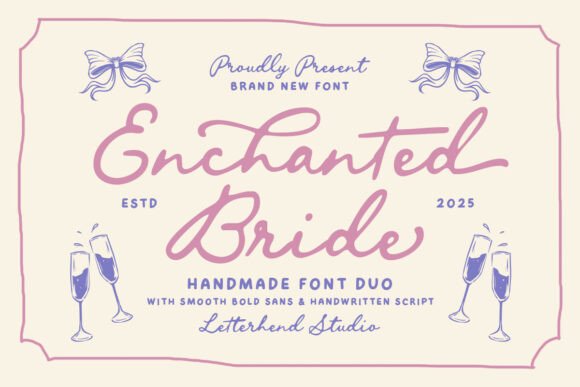
Enchanted Bride
Ya sea que estés creando productos POD (impresión bajo demanda), invitaciones de boda o gráficos para redes sociales, Enchanted Bride es una opción ideal.